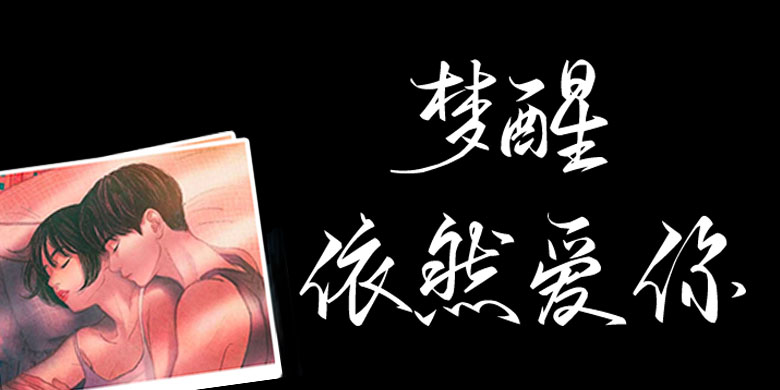
方正手迹-梦醒依然爱你
方正手迹-梦醒依然爱你,这款字体结构工整、笔画清晰,兼顾美观与易读性,适用于标题、正文、海报、包装、LOGO 等多种场景。字形优雅稳定,风格百搭耐看,适配日常排版与创意设计,让文字呈现更舒适、更具质感。方正手迹-梦醒依然爱你一笔一画,皆是细节,以均衡的比例、流畅的线条打造舒适视觉体验,字形端正大气,风格简约现代。无论是商业设计、品牌宣传还是日常排版,都能轻松驾驭,让文字更有格调与力量。方正手迹-梦醒依然爱你字体下载。
梦醒依然爱你这款字行笔劲健爽利,抑扬顿挫,富有韵律感。中宫较为紧凑,外围舒展,整体有强烈的节奏感和速度感。适用于现代诗歌、短文的排版以及文化、商业类品牌的广告语设计。